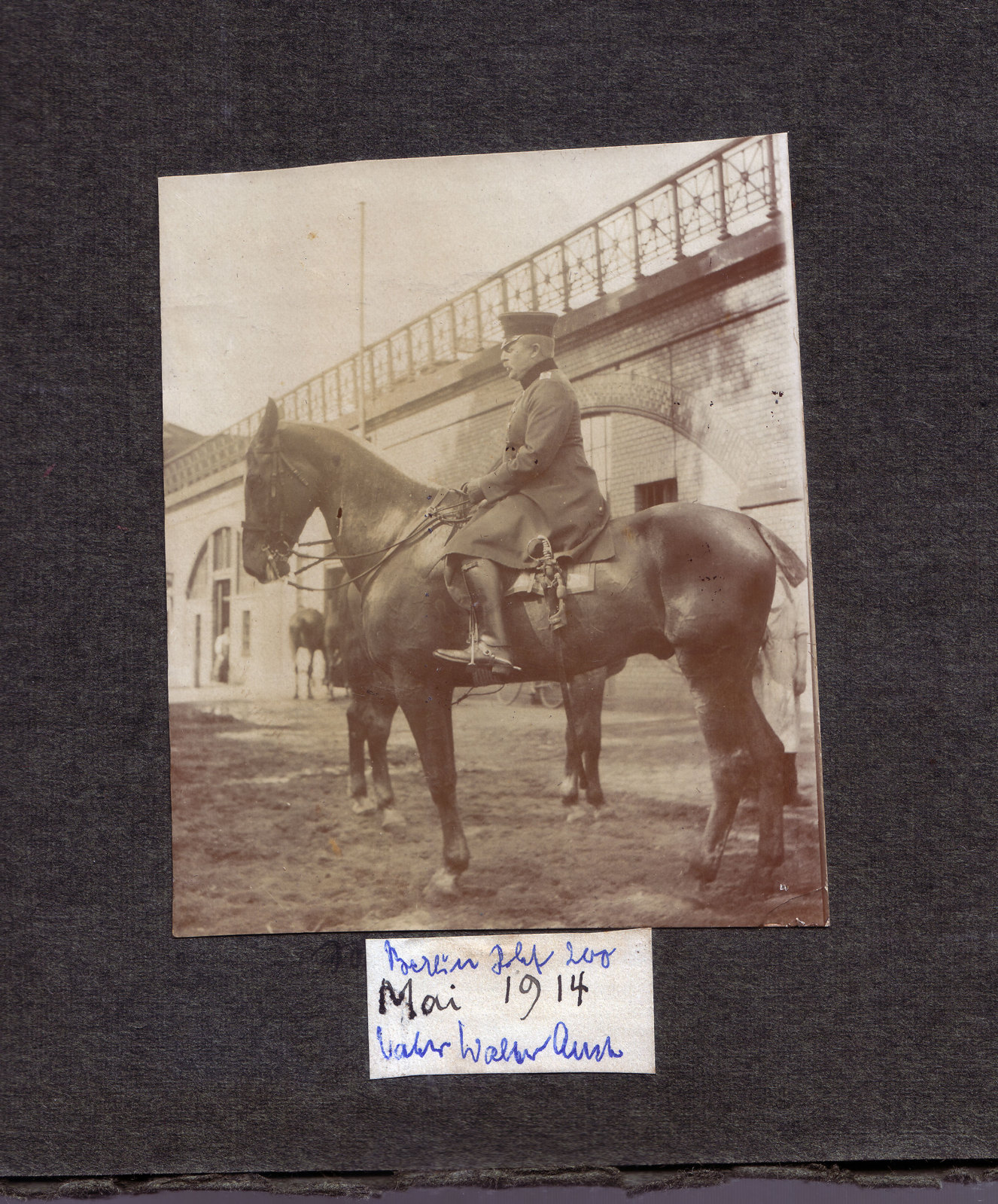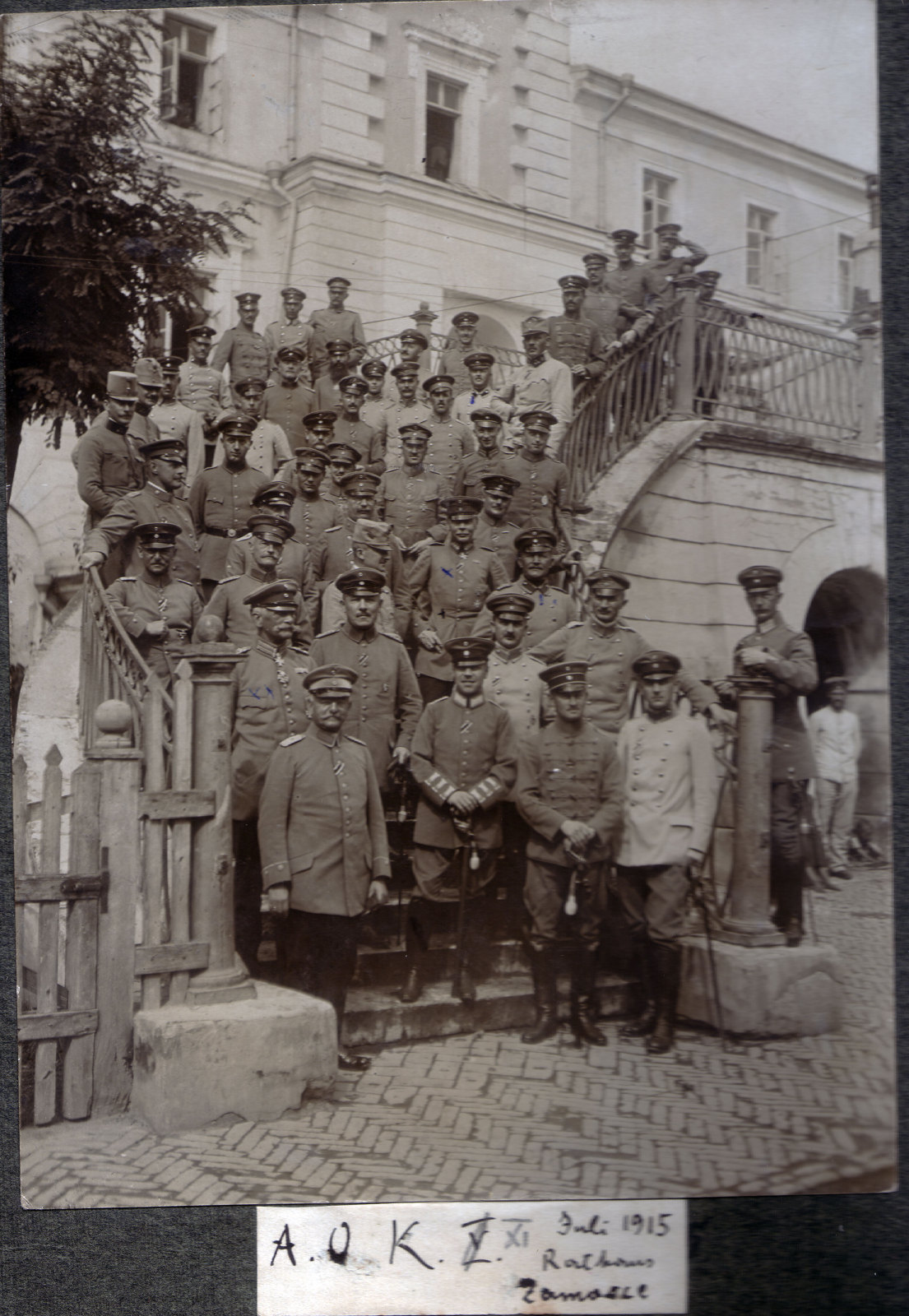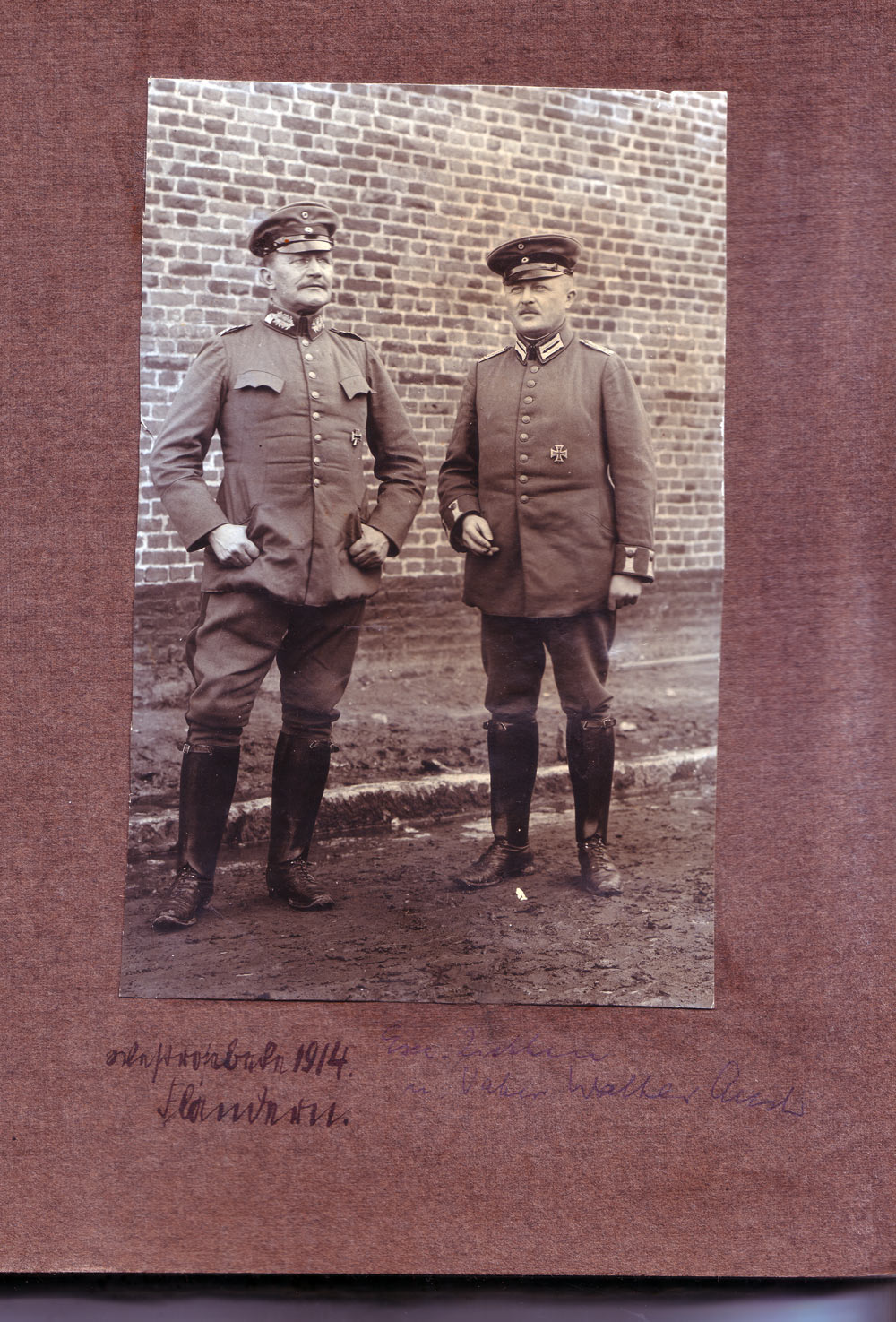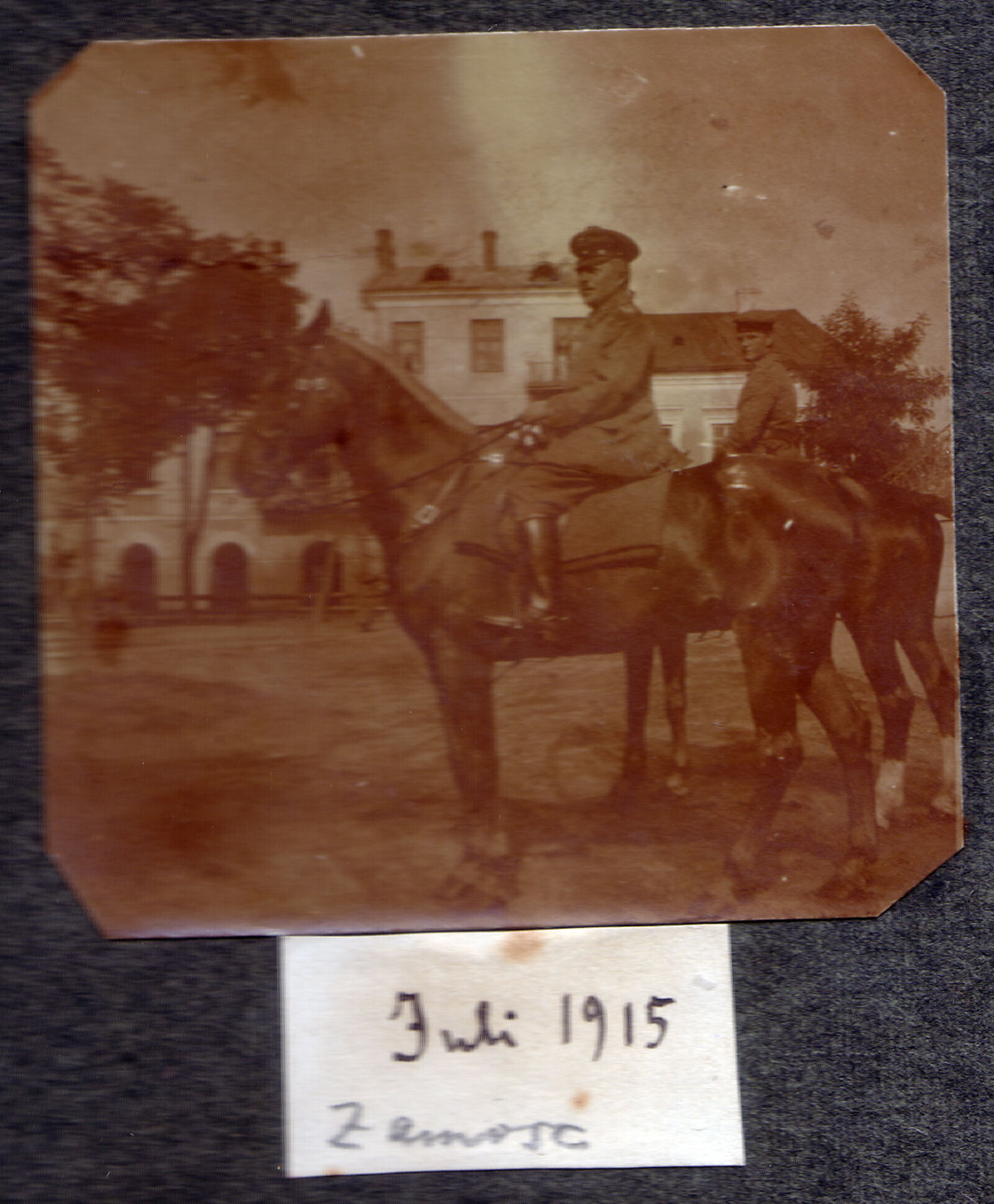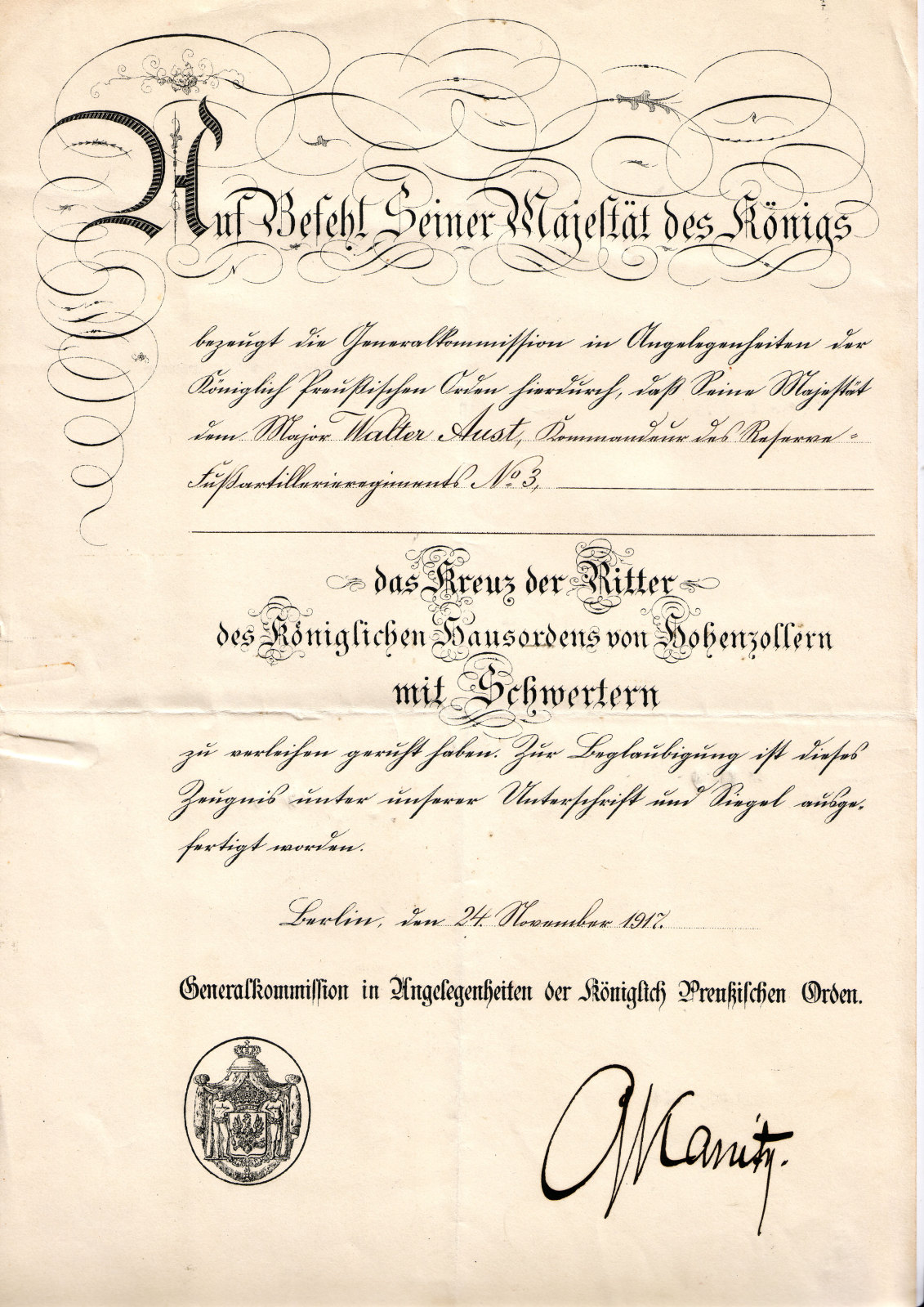
Handschriftliche Eintragungen auf Fotos (WW I), schwer zu entziffern …
Aus dem Nachlass meiner Grossmutter haben sich Fotos ihres Vaters, eines Militärs, aus der Etappe im ersten Weltkrieg irgendwo in Ostpreussen oder Polen angefunden. Auf der Rückseite sind diese beschriftet, s. Abbildungen. Könnte Hilfe gebrauchen, diese zu entziffern …
Die zweite Zeile könnte »Aussenlager Suwalki«heißen.
In der ersten und der dritten Zeile meine ich am Zeilenanfang »Arbeit…« oder »Arbeitsantritt« zu lesen.
Könnte die letzte Zeile »Innerer Ring Suwalki« heißen?
Das zweite heißt »Jugendlager Suwalki«, würde ich sagen.
Ich sehe da ein doppeltes g. Eigentlich würde ich eher »Fuggerlager« lesen, aber das scheint keinen Sinn zu ergeben.
Ich habe meinen Beitrag gerade von »Jugend« auf »Aussen« korrigiert. Ich glaube, das sind zwei s.
Und Nachtrag: Wenn ich mir das A in Augustow anschauen, dann kann das andere nicht »Arbeit« heißen, der erste Buchstabe sieht vollkommen anders aus.
Hey, Wow! Danke für eure Interpretationen! Also erst mal sorry, das ich die Bilder nicht dazu gepostet habe, weil die bringen natürlich noch zusätzliche Info …
Also erste Zeile würde ich dann, weils kein A ist »Erbeutete russ.(?) (nächstes Wort unlesbar) in Augustow« (auf dem Bild sind jede Menge Pferdefuhrwerke zu sehen) sagen.
Zweiten Zeile »Aussenlager Suwalki« wird wohl stimmen, auf dem Bild ist eine Kirche zu sehen, auf dem letzten, ganz unten ist das Innere abgebildet, also letzte Zeile »Inneres Kirche Suwalki (Gefangenenlager)«, 3. Zeile (wie erste Zeile) »Erbeutete russ.(?) (nächstes Wort unlesbar) in Suwalki«, 4. Zeile »Augustow«, 5. Zeile »Exc. von Eichhorn« (oder -born),  letzte Zeile hatten wir schon. Verbindlichsten Dank, werd sehen, das ich wenigstens noch eins der Bilder hochlade!
und das wär dann wohl »Inneres Kirche Suwalki (Gefangenenlager)«
und dies wär dann zur rechten der Urgroßvater, diesmal in Flandern, mit dem Kollegen Exc. Ziethen. Für alle Tips für das Wort vor der 1914 wär ich recht dankbar ;-)
Ich lese:
Erbeutete russ. Geschütze in Augustow
Truppenlager Suwalki [erster Buchstabe ist eindeutig ein T, die beiden Kringel ziemlich sicher ein doppeltes p]
Erbeutete russische Geschütze in Suwalki
Exc. v. Eichhorn [kurze Internetsuche legt tats. Eichhorn nahe, es sieht auch nicht nach einem b aus]
Inneres Kirche Suwalki
(Gefangenenlager)
Mir fällt auf, dass das E in "Erbeutete" (Kurrent-E?) sich von dem in "Exc. von Eichb/horn" unterscheidet. Waren hier verschiedene Schreiber beteiligt?
Namen wurden meist in lateinischer Schrift wiedergegeben (oder in einem wilden Mischmasch aus Kurrent und lateinischen Buchstaben). Und Exc. gehört wohl zu den "Fremdworten", die man ohnehin eher in lateinischer Schrift wiedergegeben hat.
Also erst mal sorry, das ich die Bilder nicht dazu gepostet habe, weil die bringen natürlich noch zusätzliche Info …
Falls Du Zeit hast, wäre das schon schön, noch die anderen Bilder zu sehen. Sozusagen als Auflösung dieses Sommerlochrätsels.
Für alle Tips für das Wort vor der 1914 wär ich recht dankbar ;-)
Westro……ke?
Mir fällt auf, dass das E in "Erbeutete" (Kurrent-E?) sich von dem in "Exc. von Eichb/horn" unterscheidet. Waren hier verschiedene Schreiber beteiligt?
Auch die s-Formen weichen stark ab, in »Geschütze« z. B. deutsch, in »Augustow« lateinisch.
Ach herrje! Suwalki taucht auch im Kriegstagebuch meines Opas auf, allerdings aus dem Zweiten Weltkrieg. Wikipedia meint zwar, dass »Suwałki lange Zeit abseits der großen Verkehrsströme« gelegen hätte, aber zu Kriegszeiten war das wohl anders.
Noch mal vielen Dank für die Aufklärung zu den Eintragungen … hier jetzt endlich die Bilder als
Auflösung des Sommerlochrätsels
in der Reihenfolge
1) Erbeutete russ. Geschütze in Augustow
2) Truppenlager Suwalki
3) Erbeutete russische Geschütze in Suwalki
4) Exc. v. Eichhorn
5) Inneres Kirche Suwalki (Gefangenenlager)
(dieses wurde schon weiter oben gezeigt, statt dessen ein Bild, Augustow beschriftet, das vermutlich russische Kriegsgefangene zeigt)
Ausserdem: das Offizierspatent und die Urkunde zum Erhalt des Hohenzollernschen Hausorden für den Oberleutnant Aust, sowie einige Bilder aus dem privaten Fotoalbum, die einmal ein Gruppenbild des Armeeoberkommandos auf den Stufen des Rathaus Zamosce zeigen (Aust ist der zweite von rechts innerhalb einer Vierergruppe mit hellen Uniformjacken, oben im Bild) und zwei Bilder zu Pferde (einmal daheim am Bahnhof Zoo in Berlin – deutlich zu erkennen die S-Bahn Bögen im Hintergrund, und dann im Dienst in Zamosce.) Die beschrifteten Fotos sind wahrscheinlich Werke von Armeefotografen, interessant wäre da noch was die Ziffern in den Bildern zu bedeuten habe, wahrscheinlich ein Hinweis auf irgendeine Art von Registratur – der Urgroßvater muss als Mitglied des Oberkommandos weit herumgekommen sein im ersten Weltkrieg, wie ja auch das Bild aus Flandern zeigt, lt. Aufzeichnungen meiner Großmutter geht auch die Bombardierung der Kathedrale von Reims auf sein Konto  – hmm – weitere Bilder dieser Art finden sich allerdings nicht im Nachlass.
Der in Berlin-Schöneberg beheimatete Oberst war nach dem 1. Weltkrieg a. D. und schloss sich auch nicht mehr der Reichswehr an. 1928 verstorben wurde er auf dem Jerusalemer Friedhof in der Bergmannstraße bestattet – der so in ca. 500 m Luftlinie von meiner Bürobeteiligung hier liegt …